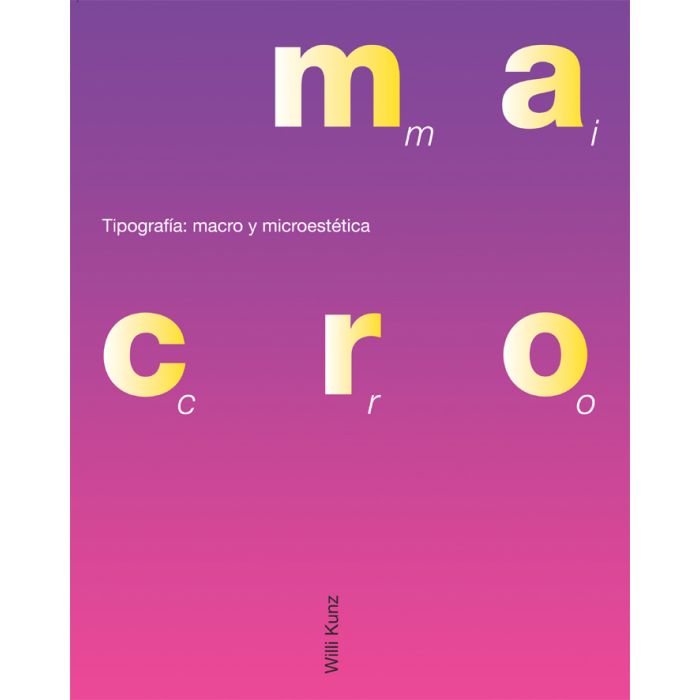
Tipografía. Macro y micro estética
Un libro de Willi Kunz
El ordenador facilita la experimentación y la utilización de tipografías creadas con criterios visuales cada vez más personales. Pero el diseño de una buena tipografía siempre se basa en ciertos principios fundamentales. Sin estos principios, la tipografía no puede comunicar, al igual que el lenguaje no podría comunicar sin la gramática, el vocabulario y la sintaxis.
Mediante el uso de estos principios fundamentales básicos, la tipografía puede alcanzar resultados muy sofisticados. Toda buena tipografía se basa pues en esos principios.
Este libro se estructura en cuatro partes: la primera parte analiza los distintos elementos tipográficos, desde las cualidades microestéticas de las letras, los números y los signos de puntuación hasta las líneas y los elementos geométricos y su diseño del espacio, la estructura, la secuencia, el contraste, la forma y la contraforma, e ilustra sus funciones con ejemplos extraídos de la enseñanza y la práctica; la tercera parte demuestra cómo los elementos tipográficos contribuyen al diseño en el nivel microestético, y la cuarta parte, a partir del análisis de una serie de carteles de arquitectura, analiza la interrelación entre el objetivo, la macroestructura y la microestética.
Contenidos: Introducción Elementos de tipografía Aspectos de diseño Macro y microestética Síntesis Apéndice |
Prefacio (extracto) La tipografía es el arte de diseñar letras y componer textos de tal modo que puedan leerse de un modo fácil, eficaz y agradable. Algunos principios fundamentales subyacen en toda buena tipografía, ya sea de periódicos, revistas o libros, o bien de carteles, envases o pantallas de ordenador. Estos mismos principios, establecidos primero en los tipos móviles de Gutenberg y desarrollados más tarde con las revoluciones visuales modernas, serán todavía válidos en la nueva era de los medios electrónicos: hipertextos, Internet…, sean cuales sean los foros que el futuro pueda traer consigo. Este libro presenta los principios permanentes de la tipografía, explica cómo aplicarlos e ilustra su potencia y su versatilidad con ejemplos tomados de mis veinticinco años de experiencia profesional. Al demostrar cuál es la forma de poner en práctica la teoría, Tipografía: macro y microestética proporciona formación artística y técnica para los diseñadores tipográficos, los arquitectos y los profesionales de otros campos afines. Además, al analizar el papel que el diseño gráfico desempeña en la cultura actual, dominada por los medios de comunicación, facilita una valoración más crítica no sólo del primer plano de mediación, sino también de su contexto no codificado, y de las diversas relaciones que vinculan a uno y otro. La mayoría de los libros sobre tipografía sólo muestran el producto final; no dicen nada ni sobre el proceso de diseño ni sobre los principios que lo han guiado. Los anuarios de diseño y las revistas de papel couché no son mejores: los primeros no son más que recopilaciones vanidosas, las segundas nada más que ráfagas de estrellas y tendencias destinadas a haber dejado de brillar cuando salga el número siguiente. En un movimiento circular, los estudiantes imitan a las estrellas, los diseñadores siguen tendencias, los clientes sondean los mercados y el público se ahoga en un enorme "océano" gráfico sin lograr nunca aprender cómo detectar y observar la buena tipografía. Este libro proporciona los instrumentos de navegación para trazar nuevos derroteros a través de la inundación de información que nos rodea hoy en día. La Era de la Información ha llegado. Y aunque con ella se había pronosticado -una vez más- la muerte de los medios impresos, el papel continúa bien vivo. En los años treinta y en los años cincuenta se decía: "Esto significará el fin de aquello". Pero ni la radio primero ni la televisión más tarde acabaron con los periódicos, las revistas, los libros. Y en los ochenta tampoco la oficina conectada en red dio lugar a la oficina sin papeles. Por el contrario: en nuestros hogares, en nuestros lugares de trabajo y en el tránsito diario entre unos y otros, se espera que todos nosotros procesemos una cantidad cada vez mayor de información impresa sobre papel. En consecuencia, no sólo tenemos cada vez menos tiempo para leer con atención cada elemento, sino que además, de forma concomitante, estamos cada vez menos dispuestos a esforzarnos en interpretar material pobremente presentado. Por ello no es de extrañar que haya tantos documentos impresos destinados a un uso efímero; constituyen los desechos flotantes de nuestra civilización. Si el problema es el papel impreso, entonces, ¿acaso son los medios electrónicos la solución? Sí y no. Los libros y los ordenadores responden, unos mejor que los otros, a propósitos diferentes. Los ordenadores son el medio idóneo para buscar pequeñas porciones de información en fuentes que son muy amplias, que cambian constantemente o bien son individuales en extremo: bases de datos, cuotas de mercado e informes empresariales, por ejemplo. También conllevan la ventaja añadida de que los residuos se convierten en éter, y no en un vertedero de basuras. Sin embargo, los ordenadores no constituyen el mejor medio para leer textos largos que exijan una implicación; la mayoría de las personas, antes de pasarse horas interminables escrutando en una pantalla de ordenador, preferirán imprimir los documentos y trabajar sobre la copia impresa: en realidad, "publicarán" una página, un capítulo, un libro editado individualmente. Los libros son un formato familiar. Son fáciles de usar y de transportar; no requieren ningún software complicado, ningún hardware caro para poder funcionar. Los libros complementan los placeres literarios de un texto con otras satisfacciones sensuales adicionales: las calidades visuales, táctiles y estéticas del papel, la tipografía, la impresión y la encuadernación. Además, los libros tienen un "aura"; en una estantería, imparten cierta sensación de comunidad intelectual y continuidad histórica que los CDs colocados en un porta CDs, simplemente, no tienen. Tienen otra sutileza. Aunque los libros siempre serán los ejemplares definitivos de la tipografía impresa, los medios electrónicos muestran palabras e imágenes cuyo diseño también debe ser coherente y convincente para el observador pasivo. Los medios interactivos requieren, además, que el diseño sea comprensible y conveniente para el usuario activo. El hipertexto constituye un caso extremo en el que el diseño del original debe estar estructurado de forma tan completa que pueda adaptarse a cualquiera de sus posibles deconstrucciones y a todas ellas, así como a cualquier reordenación o idiosincrasia de sus innumerables "autores" individuales. Irónicamente, esta estructura sólo puede proceder de los principios fundamentales de la tipografía, que se formularon por primera vez en la Biblia de Gutenberg en 1455. Hoy en día es importante establecer una distinción entre los principios visuales fundamentales y las convenciones técnicas tradicionales. Muchas de estas convenciones surgieron en los tiempos en que el diseño y la composición de textos eran dos profesiones independientes, y la coordinación entre ambas exigía especificaciones exactas sobre el tipo y el cuerpo de letra, la longitud de la línea, etc. De forma inevitable, estas especificaciones acabaron convirtiéndose no sólo en medios para la comunicación, sino también en finalidades en sí mismas; es decir, en criterios impersonales y técnicos según los cuales era posible diseñar y valorar una tipografía. Las facilidades que ofrece el software para el diseño gráfico digital han aunado el papel desempeñado por la persona que componía los textos y el del diseñador, y han eliminado la necesidad que tenían de guiarse por convenciones técnicas tradicionales. Ahora la tipografía se crea de acuerdo con criterios más visuales, más personales. No obstante, los criterios siguen siendo cruciales; sin estos principios fundamentales la tipografía no podría seguir comunicando visualmente, del mismo modo que el lenguaje, sin la gramática y el vocabulario, no podría seguir comunicando verbalmente. La tipografía: macro y microestética elabora estos principios. En concreto, este libro analiza en primer lugar el espacio, la estructura, la secuencia, el contraste, la forma y la contraforma; a continuación expone cómo pueden sintetizarse estos elementos para crear un cuerpo de texto tanto impreso como en soportes electrónicos. - Willi Kunz |